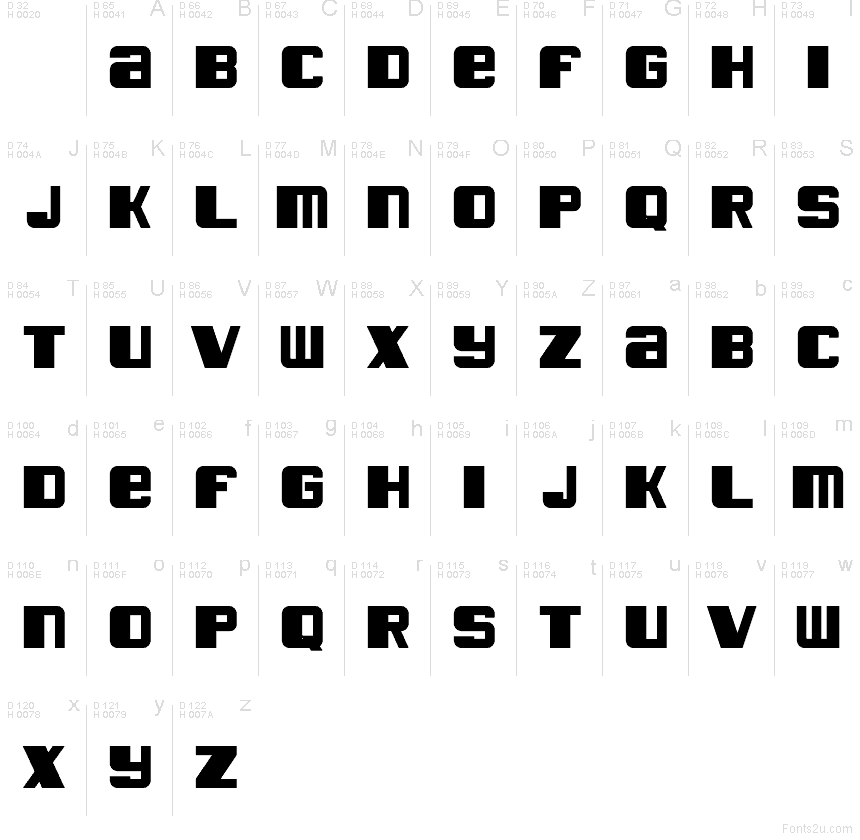
Leprosy Armadillo od Vladimira Nikolicie je bezplatné techno display písmo, tvorené ťažkými, kompaktnými znakmi so zjemnenými vonkajšími rohmi. Hranaté výrezy a tupé rezy vytvárajú modulárny, mechanický rytmus, zatiaľ čo zaoblené siluety dodávajú písmu prístupnejší, nie čisto industriálny charakter.
Husté tvary písma sú vhodné pre herné logá, vizuály elektronickej hudby, plagáty na podujatia, streetwearovú grafiku a sci-fi titulky. Využite toto bezplatné písmo na krátke nadpisy alebo titulné texty, kde tesné rozostupy a bloková konštrukcia dodávajú krátkym slovám živý a výrazný grafický vzhľad.